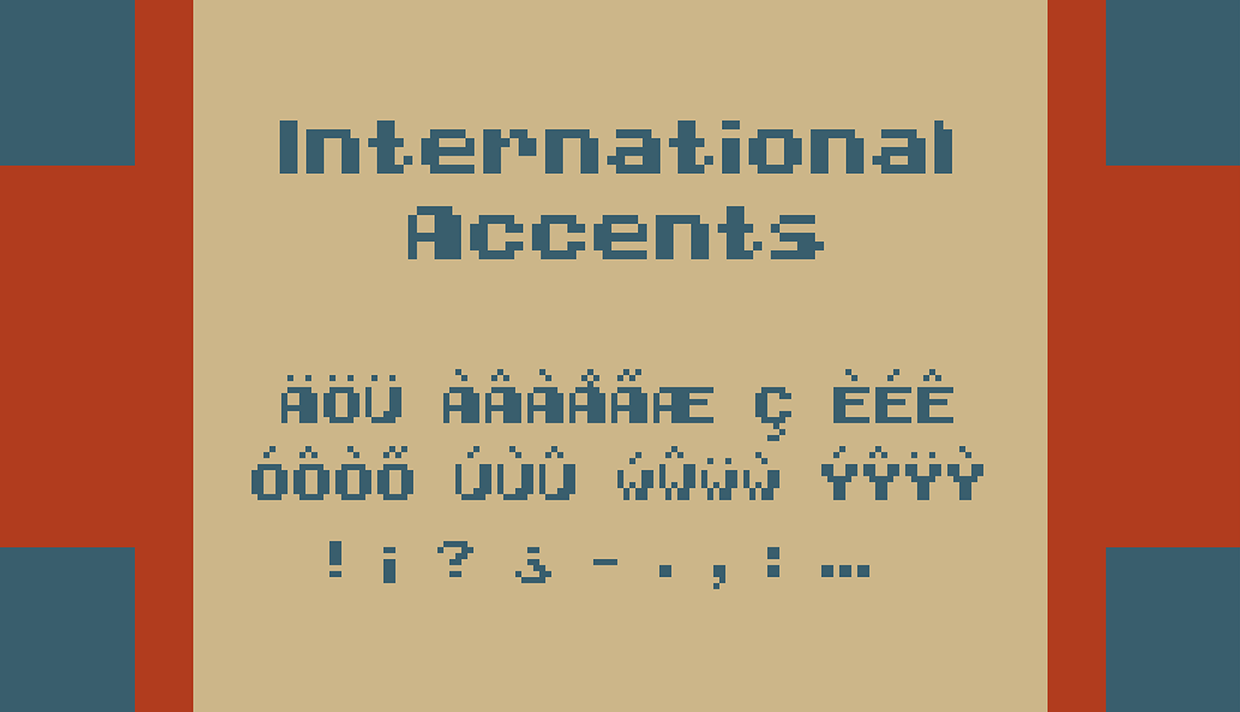
La tipografía elegida para hoy os va a traer buenos recuerdos a aquellos diseñadores que crecisteis en los años 80’s. Esos primeros videojuegos de la época 8 bit creados a base de pixeles, usaban esta fantástica fuente. Masaaki, una tipografía pixel perfecta para esos proyectos que requieren de una estética pixel.